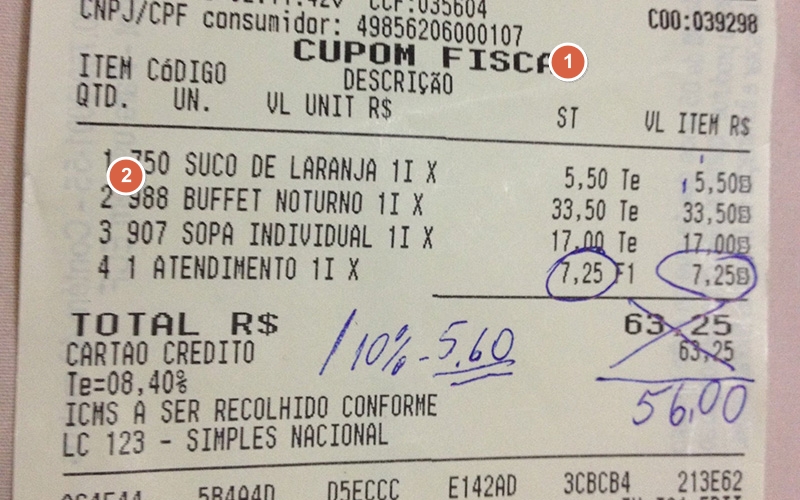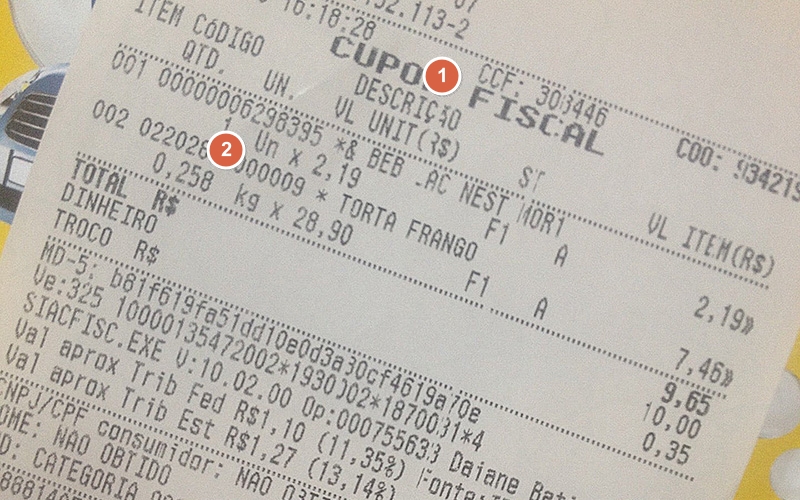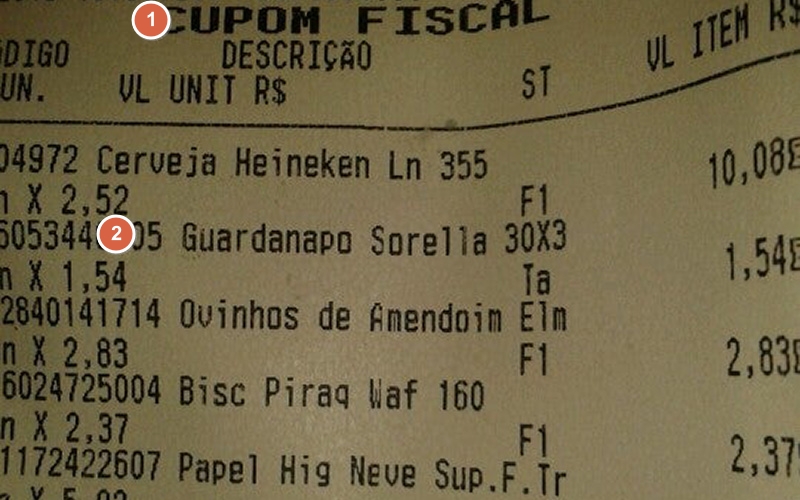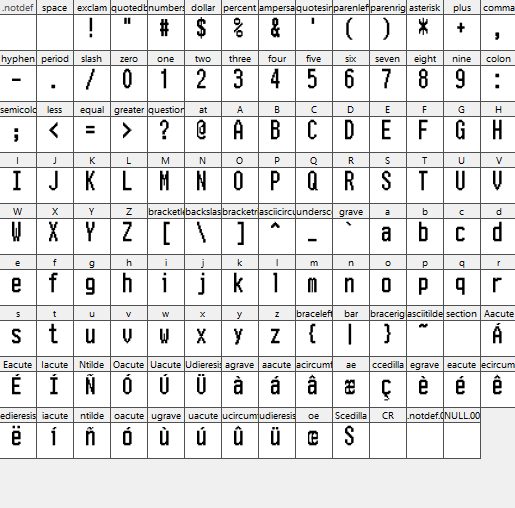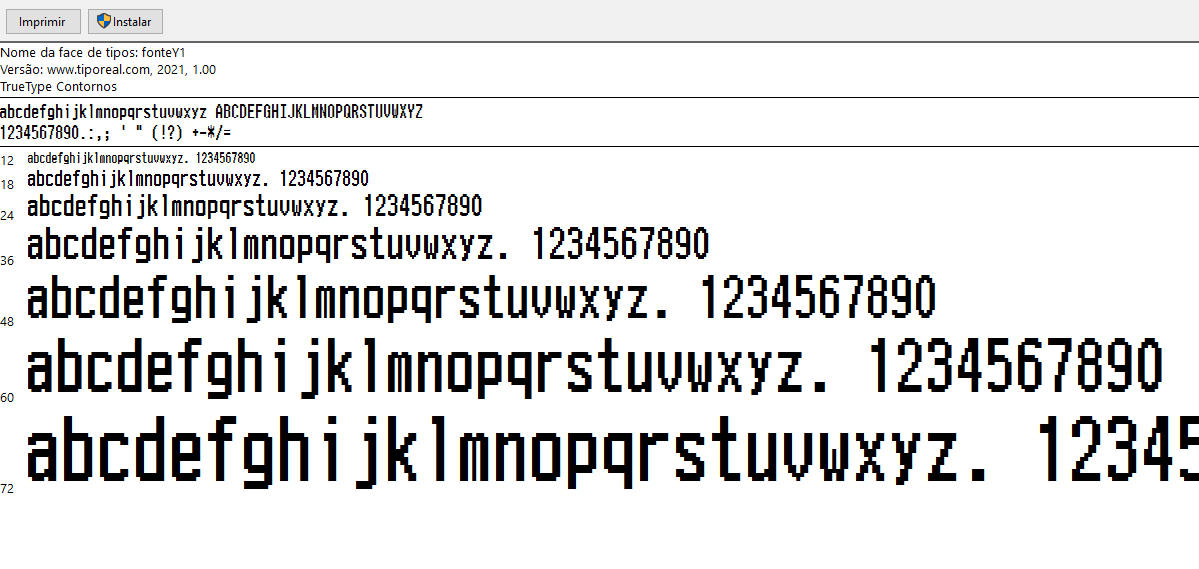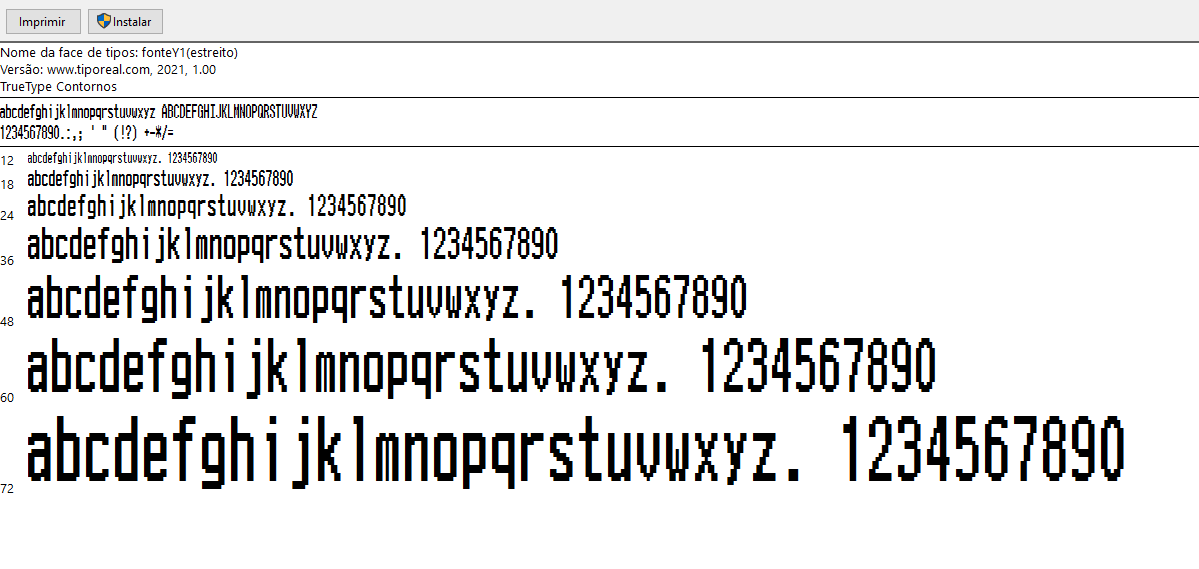
Amostra impressa da fonteY1 para cupom fiscal em Brasil (❶fonteY1-largo ❷fonteY1)⤴
Amostra impressa da fonteY1 para cupom fiscal de um correio em Brasil (❶fonteY1-largo ❷fonteY1)⤴
Amostra impressa da fonteY1 para cupom fiscal de supermercado Juzan em Brasil (❶fonteY1-largo ❷fonteY1)⤴
Todos os personagens⤴
O que parece quando aberto com o visualizador de fontes padrão do Windows⤴